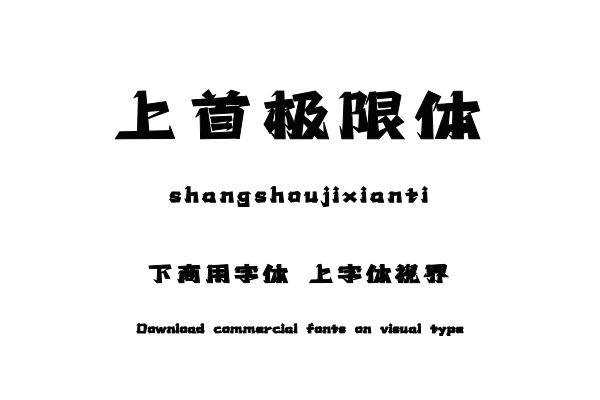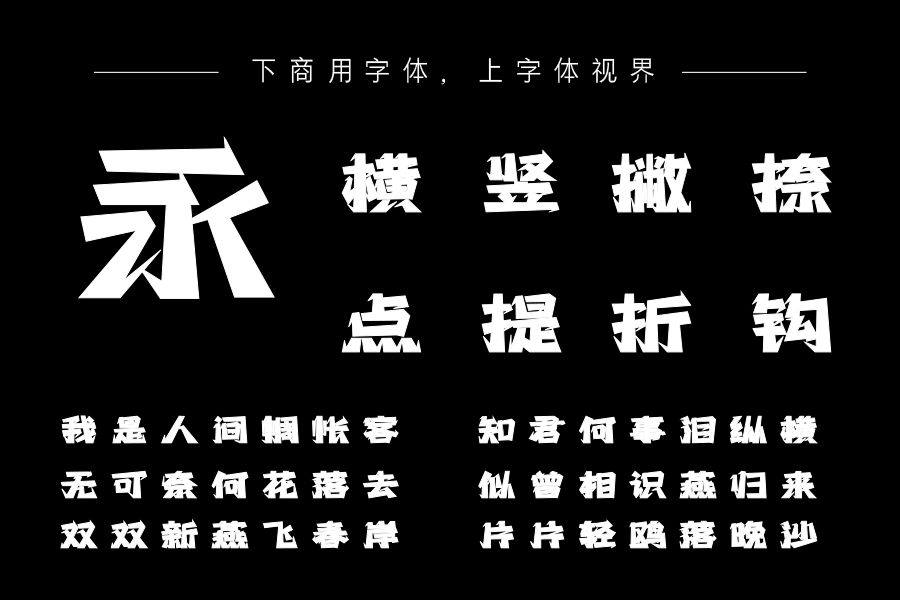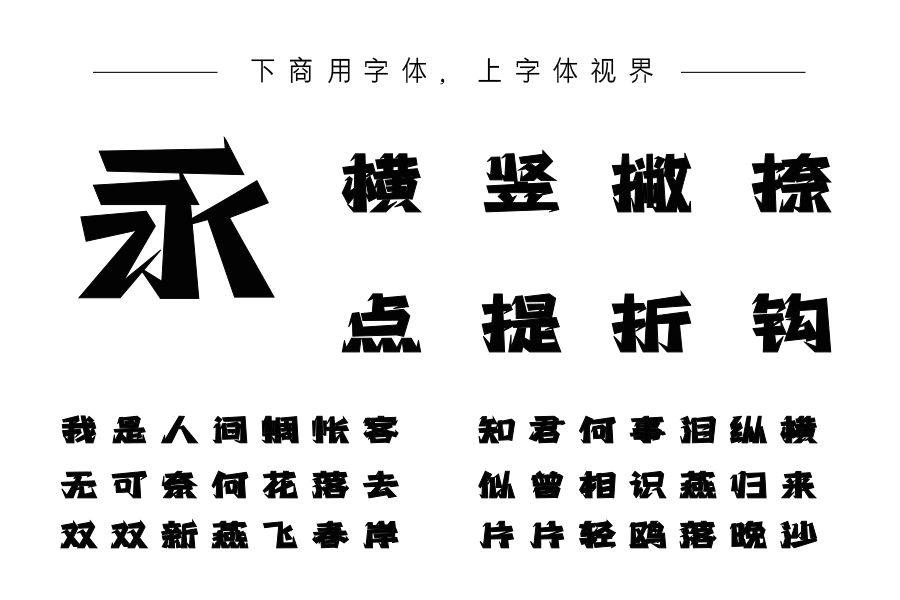
上首极限体,字体潇洒俊逸。整体风格豪放起笔和折笔处斩钉截铁,气势上扬,形成了力量与和速度的极限之感。适用于搭配标志、广告标语、商业广告等高端属性。购买须知:“下载服务费”与“字体VIP”所获得字体 仅用于个人非商用, 商用请联系付费授权。本字体为电脑用字,手机没有root权限不支持直接手机换字(手机如何root,请自行百度搜索教程)。购买前请先 了解清楚后再付款 ,字体为虚拟产品无法回收 一旦购买不支持退款。